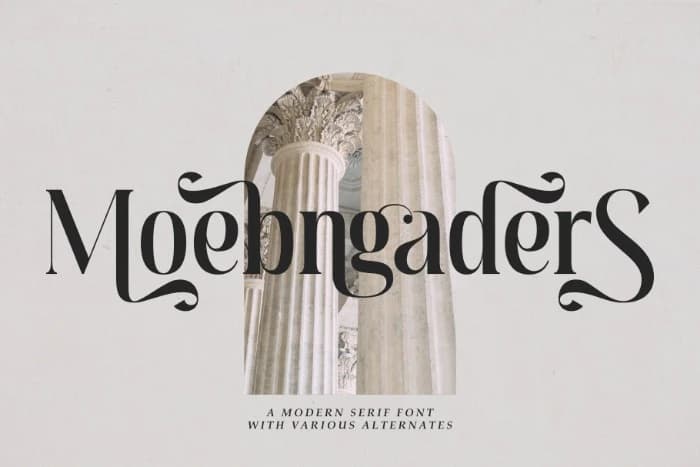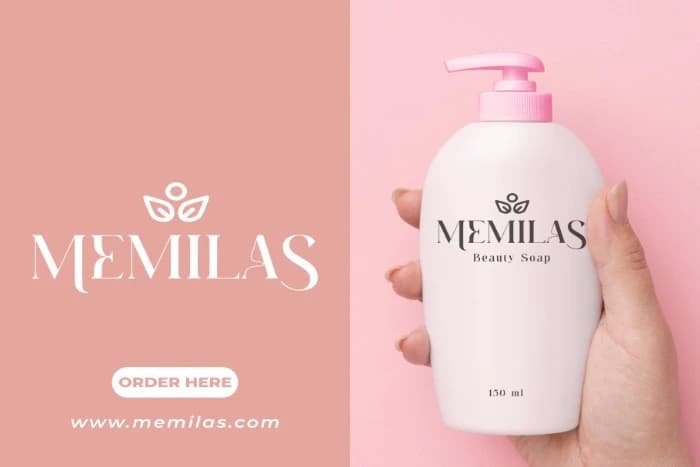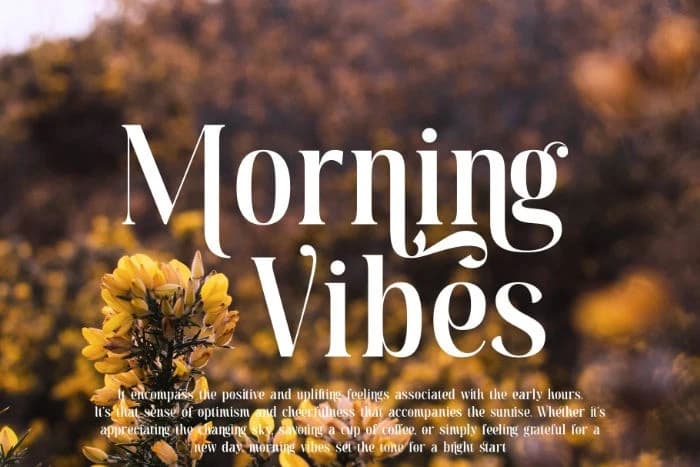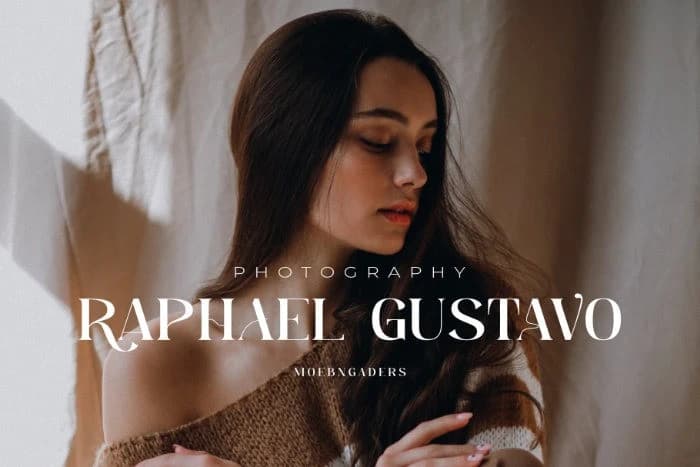
Moebngaders Font
Moebngaders Font zarafeti güçle kusursuz bir şekilde birleştiren modern bir serif yazı tipidir. Bir marka kimliği oluşturuyor, bir logotip tasarlıyor veya çeşitli yaratıcı projelere girişiyorsanız, Moebngaders güvenilir yol arkadaşınızdır.
Moebngaders Font, zarafeti güçle sorunsuz bir şekilde birleştiren modern bir serif yazı tipidir. Bir marka kimliği oluşturuyor, bir logotip tasarlıyor ya da çeşitli yaratıcı girişimlere atılıyorsanız, Moebngaders güvenilir yol arkadaşınızdır.